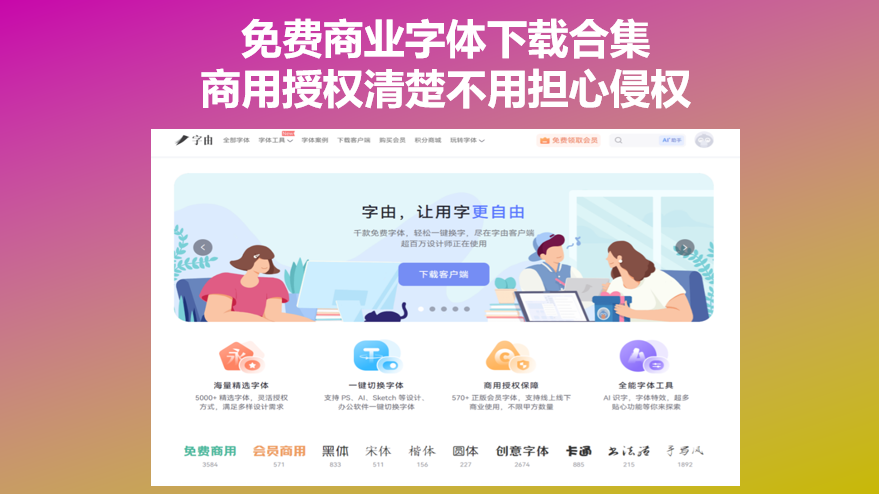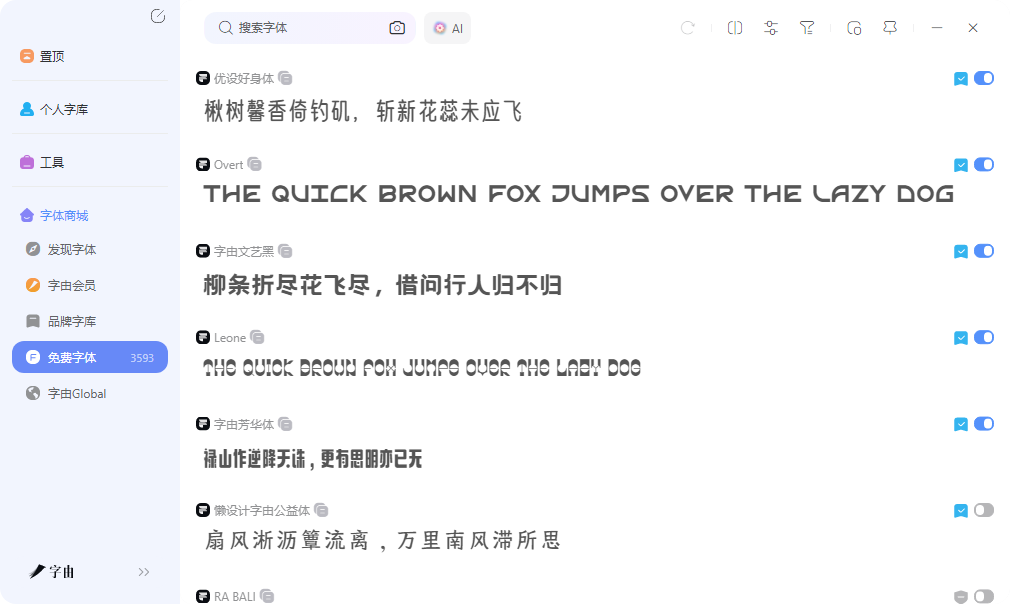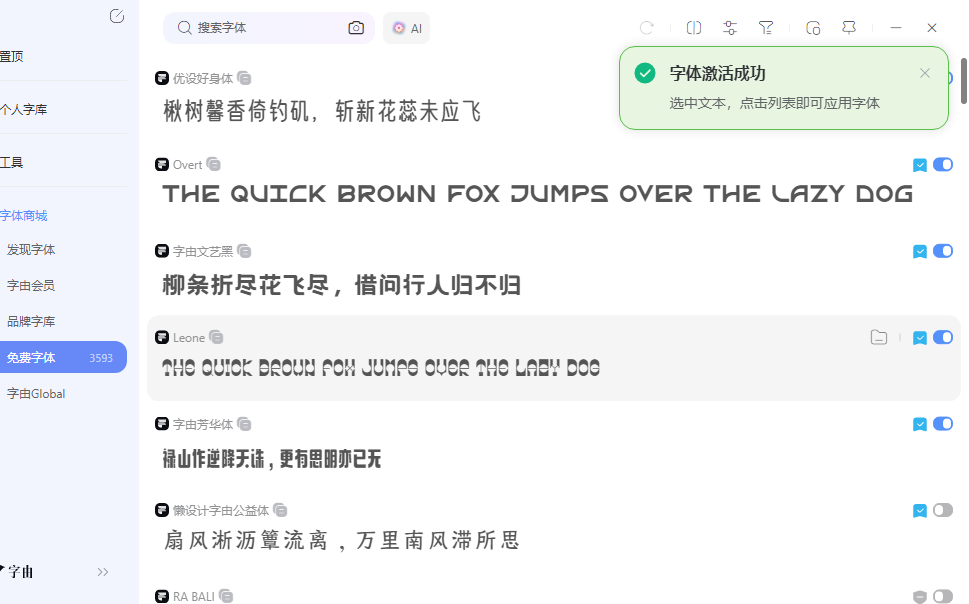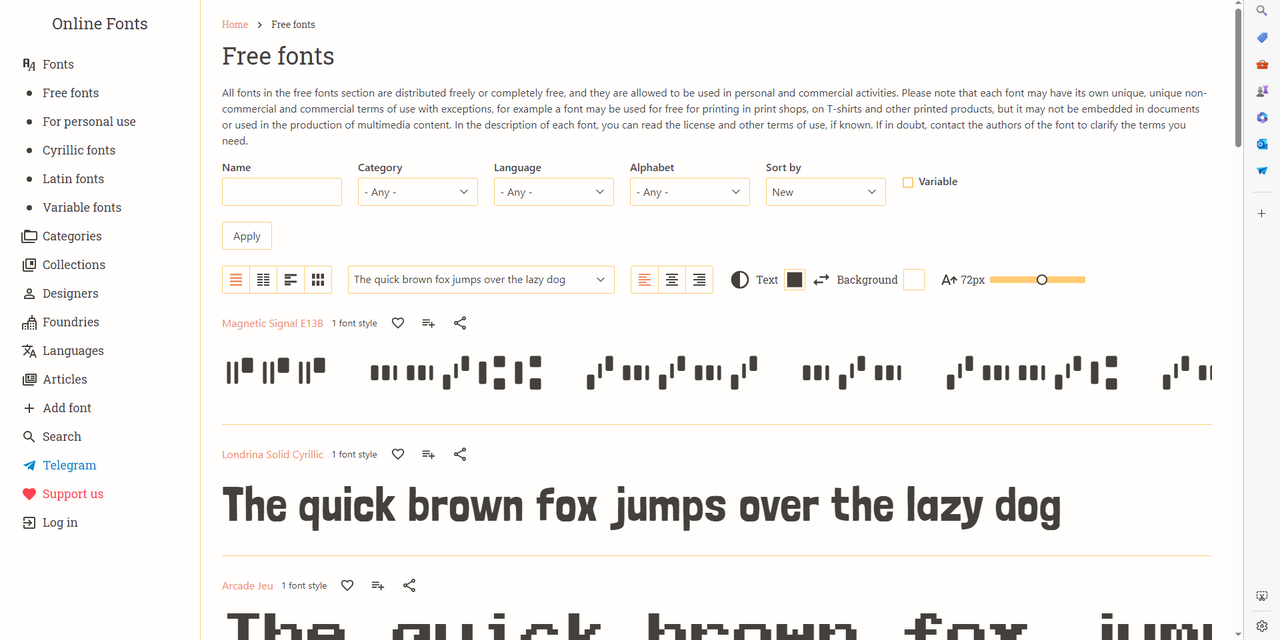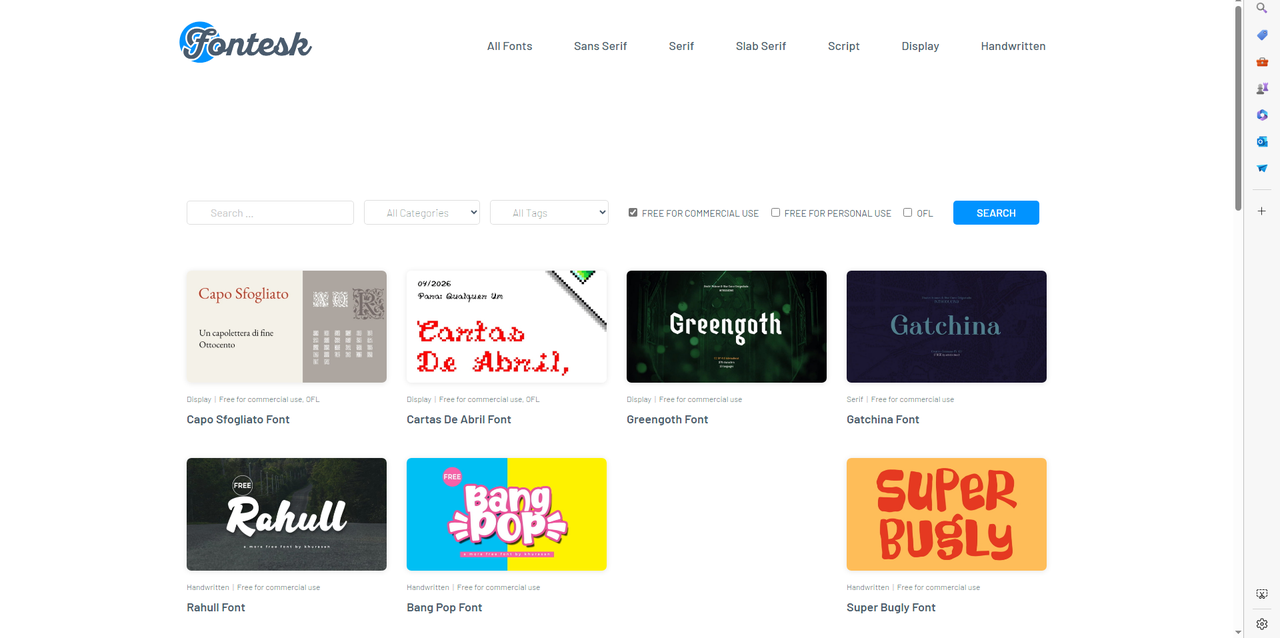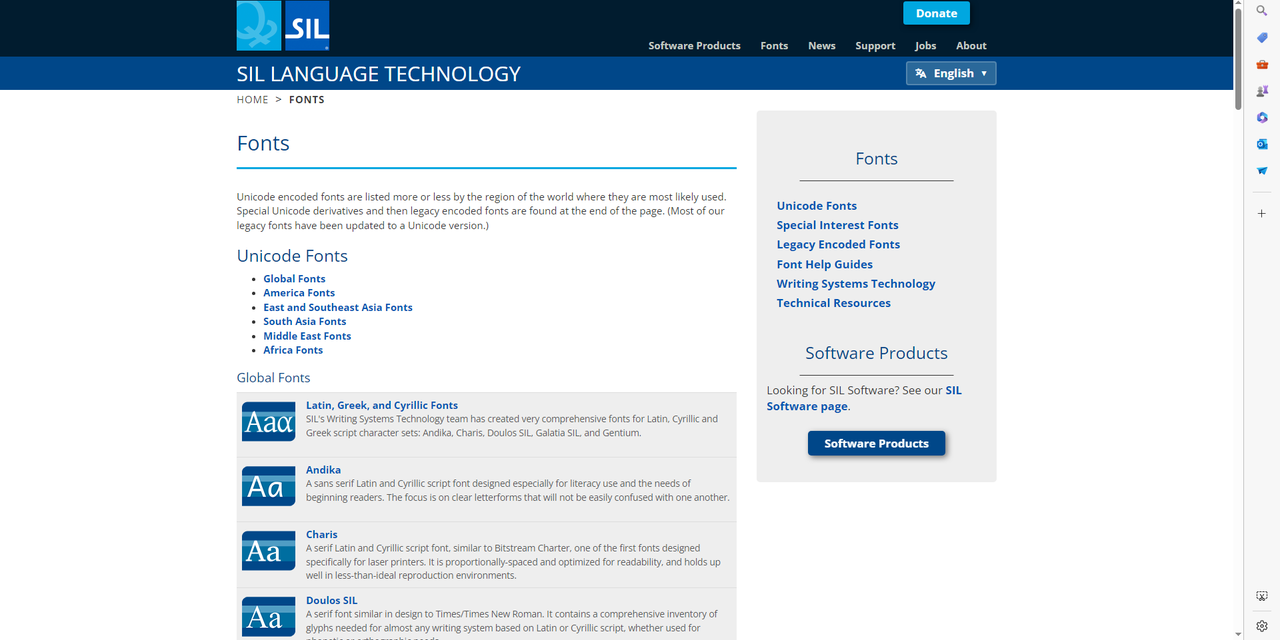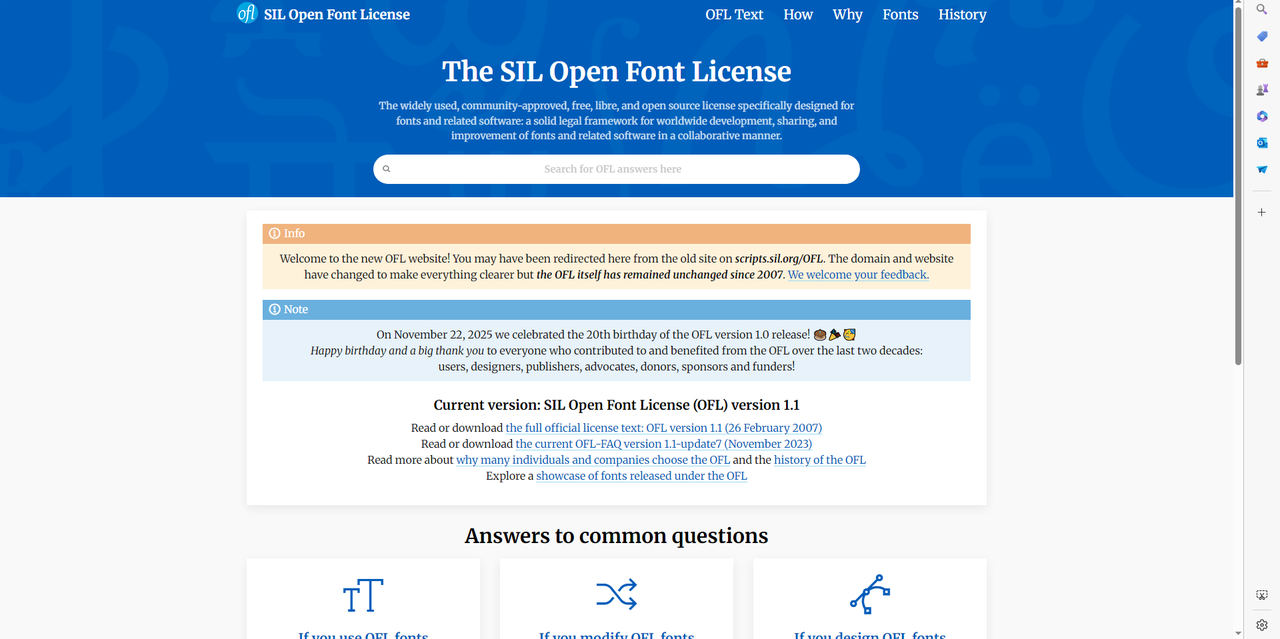
免费商业字体下载合集,商用授权清楚不用担心侵权
做商业项目时选字体,授权问题是一个绕不开的环节。很多设计师都有过这样的经历:项目做到一半,客户问这款字体能不能商用,才发现下载时根本没注意授权条款。有些字体个人使用免费但商用需要付费,有些需要标注作者信息,有些则完全禁止商业用途。事后补授权既耽误进度又增加成本,不如一开始就找免费商业字体下载渠道明确的平台。这篇文章整理的五个网站,在商用授权信息的透明度和可靠性方面都比较放心。
传统流程是去网站搜索、下载安装包、解压、安装到系统、打开设计软件确认效果,不合适再重复一遍。字由把这个过程压缩为浏览、预览、激活三步。
浏览环节有免费商用标签,勾选后列表里只显示允许商业使用的字体,不需要逐个翻详情页确认授权。超过三千款免费商用字体在这个筛选范围内,覆盖了黑体、宋体、手写体、卡通体等基础类型,以及文艺、商务、科技、复古等风格方向。预览框支持输入自己的文案,调整字号和背景色,看到合适的效果再激活。激活后字体直接出现在Photoshop、Illustrator、PowerPoint等软件的字体列表里,不需要重启软件。
对于同时处理多个项目的设计师来说,这种效率提升很明显。A项目需要商务风格标题,B项目需要文创气质的手写体,C项目需要科技感的无衬线体,在字由里分别筛选激活即可,各项目之间不会互相干扰。跨设备同步进一步减少了重复劳动,公司电脑上整理的常用商用字体分组,回家登录同一个账号全部都在,换设备不丢资源。
网页版也能完成大部分操作,临时在其他电脑上需要出图时,打开浏览器就能浏览和激活已整理的免费商业字体下载资源。客户端和网页版的数据互通,这种灵活性对经常在不同设备间切换的设计师来说比较实用。
2、Online Fonts
Online Fonts在免费字体领域是一个比较省心的选择。平台明确说明所有免费字体均可用于个人和商业用途,不需要逐个确认授权条款。这个透明度在免费字体网站中并不多见,很多平台虽然标注"免费",但商用时还有各种附加条件。筛选体系做得比较实用,支持按Category、Language、Alphabet、Sort by等维度交叉过滤,还有一个Variable选项可以筛选可变字体。预览区域支持输入自己的文案查看效果,字号可调到72px,方便判断在大标题场景下的表现力。左侧导航有Fonts、Categories、Collections、Designers、Foundries、Languages等分类,找特定风格或特定语言的字体时路径比较清晰。
平台收录的字体风格多样,这种多样化的选品让Online Fonts作为免费商业字体下载渠道,能够满足不同类型项目的需求,授权明确更是省去了后续确认版权的麻烦。
3、fontesk
Fontesk的核心优势在于商用授权的筛选机制。页面顶部的搜索区域直接提供了"FREE FOR COMMERCIAL USE"复选框,勾选后再点SEARCH,结果列表里全是允许商用的字体。这种一步到位的筛选方式比先找字体再逐个确认授权要高效得多。平台上展示的字体风格覆盖面较广,每款字体都在缩略图下方标注了"Free for commercial use"和授权协议类型(如OFL),商用信息一目了然。Fontesk的更新频率不错,经常能看到新上架的字体。对于需要免费商业字体下载资源、且希望授权信息清晰透明的用户来说,这里的筛选机制和标注规范比较可靠。建议定期来看看有没有新上架的商用免费字体,保持字体储备的更新。
4、SIL Language Technology
SIL Language Technology是一个非营利语言技术组织,专门为全球少数民族语言提供技术支持和资源。平台上的字体全部免费,采用SIL Open Font License(OFL)开源授权协议,允许个人和商业使用,也可以修改和重新分发。
字体按地区做了分类,Global Fonts覆盖拉丁、希腊和西里尔字母系统,America Fonts覆盖美洲原住民语言,East and Southeast Asia Fonts覆盖东亚和东南亚语言,South Asia Fonts覆盖南亚语言,Middle East Fonts覆盖中东语言,Africa Fonts覆盖非洲语言。这种按地域组织的体系在处理多语言项目时比较实用,可以快速找到特定语系的字体资源。
代表性字体包括Andika(专为识字教育设计的无衬线体,字母形态清晰不易混淆)、Charis(针对激光打印优化的衬线体,在低质量印刷环境下表现稳定)、Doulos SIL(类似Times New Roman的经典衬线体,字符集覆盖全面)。这些字体虽然不是为设计美学而生,但在功能性和覆盖面方面做得很好,对需要处理非拉丁文字系统的免费商业字体下载用户来说,SIL Fonts是一个可靠的补充渠道。
做中文商业项目,字由的免费商用筛选和一键激活在效率和便捷性方面表现突出,三千多款商用字体覆盖主流设计需求,作为免费商业字体下载的主力渠道比较省心。Online Fonts授权透明、筛选实用,适合英文商用字体的批量获取。Fontesk的商用免费筛选机制一步到位,上新频率也不错。SIL Fonts适合多语言项目和非拉丁文字需求。了解OFL协议的规则,遇到新平台时能自主判断授权可靠性。几个渠道搭配起来,商用字体这块基本不会出什么问题。